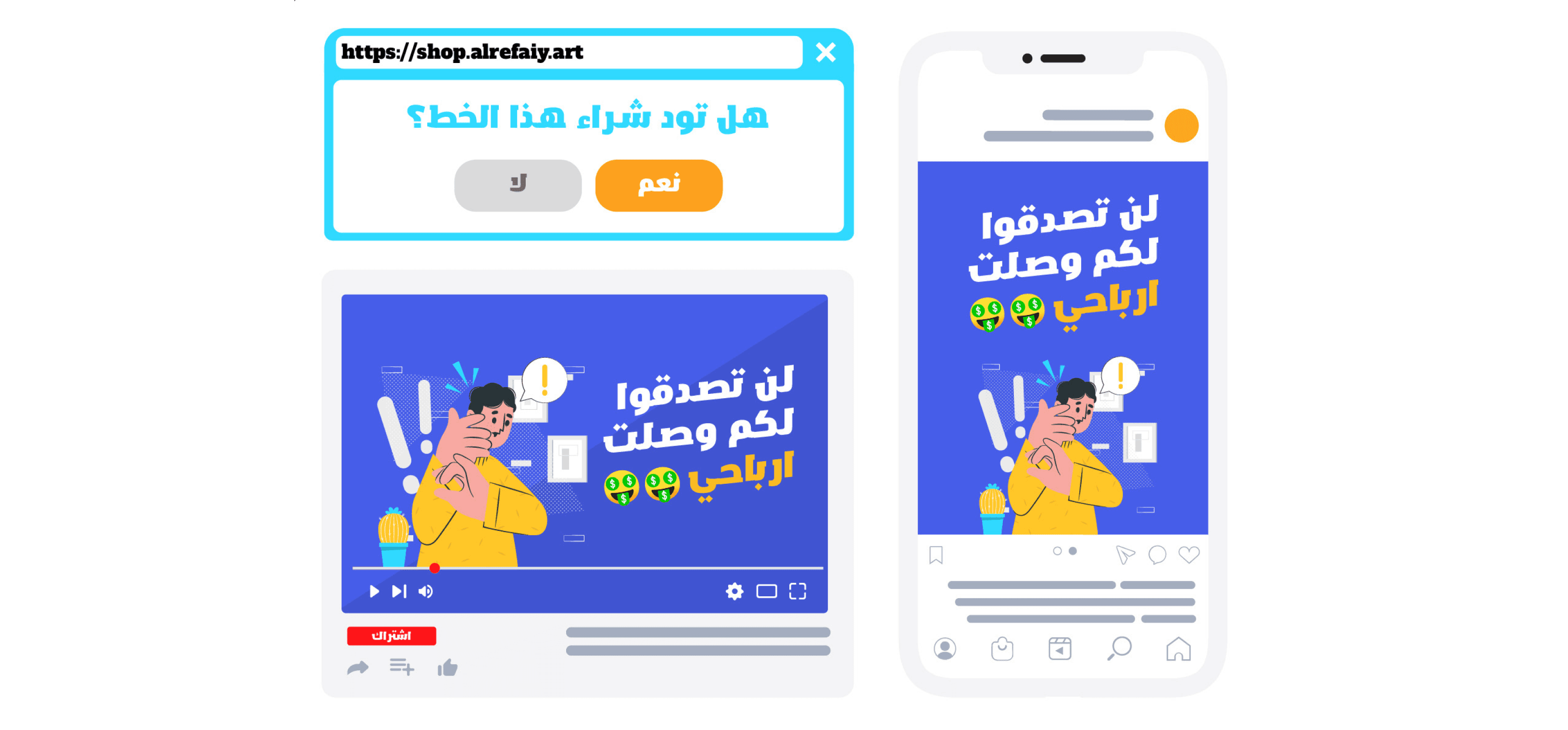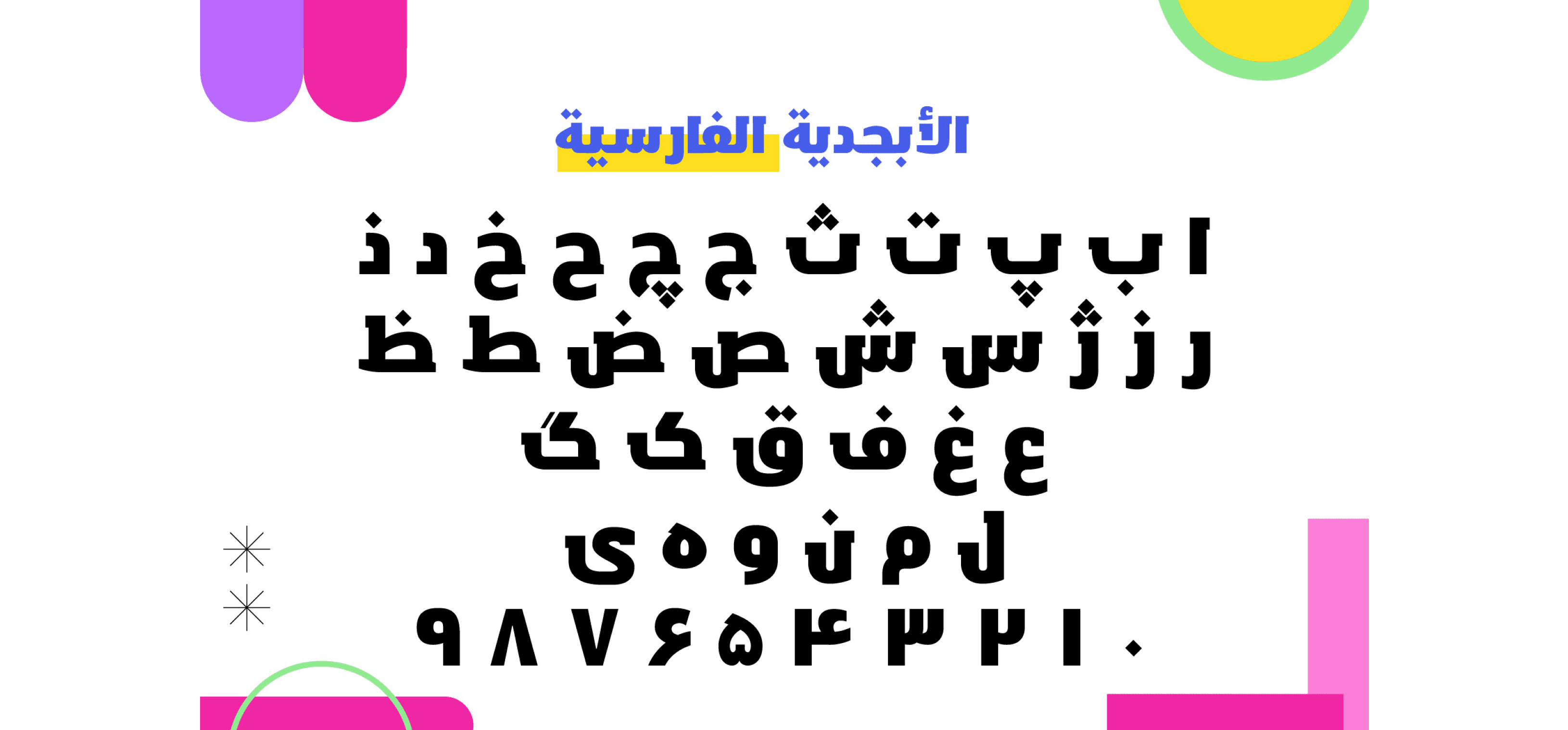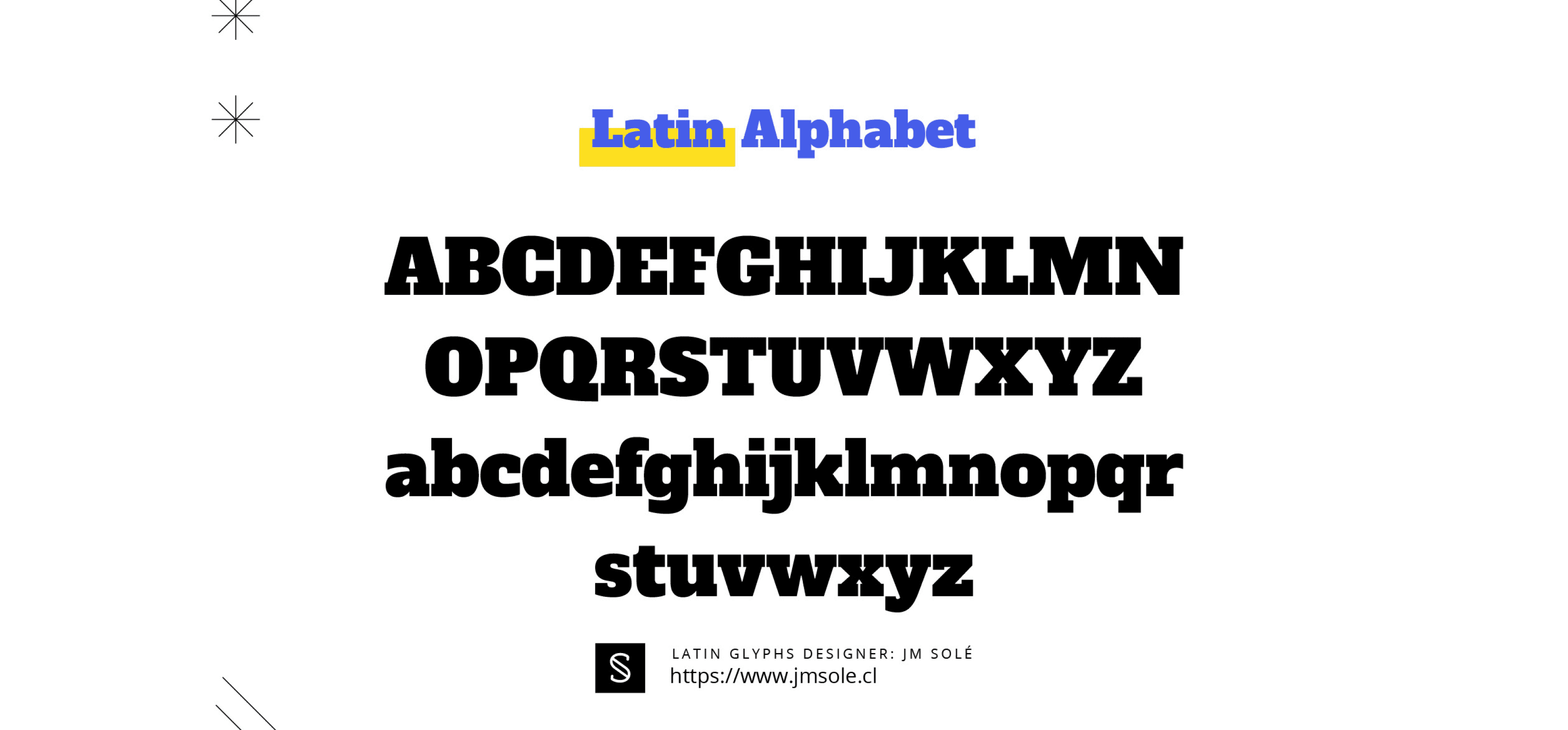
تم تصميم هذا الخط بسيريفات كبيرة، ووزن جذوع بارز، وتباين عالي في السماكات، ونهايات ناعمة تتضمن سيريف كتلي موحد. وقد تم ابتكاره من قبل يوسف رفاعي وJM Sole.
يضم الخط مجموعة أنيقة وجريئة من الحروف، تشمل الأحرف الكبيرة والصغيرة، الأرقام، علامات الترقيم، الحروف البديلة، الرموز، الأيقونات الحديثة، ومجموعة متنوعة من الرموز الخاصة، مما يجعله حزمة متكاملة مناسبة لمشاريع التصميم المتنوعة.